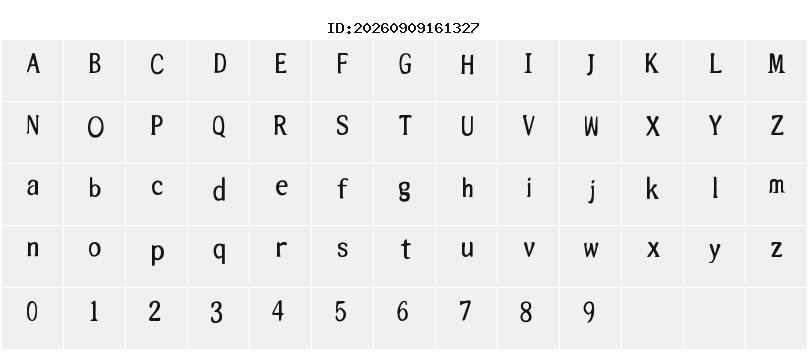
大萌宋 Preview
• Designer: 曾颖欣
• Description: 大萌宋由小欣大萌设计萌萌的宋体,《大萌宋》是一款温润仿宋,不仅承载着历史的厚重,更在现代设计的舞台上绽放异彩。其独特的温润质感,仿佛能穿越时空,将古人的风雅与现代审美巧妙融合。【诗:大萌宋体古悠长,仿宋神韵入词章。字迹如玉显温润,墨香似兰透芬芳】